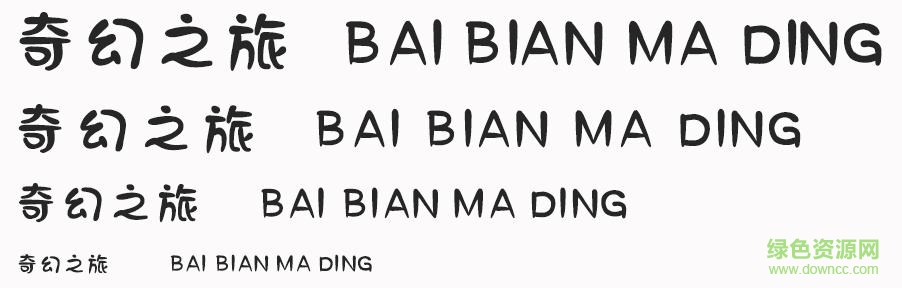
印品百變馬丁字體
印品百變馬丁字體是一款有印品字庫開發(fā)的動畫字體,喜歡看百變馬丁的朋友們不要錯過了,字里行間都是馬丁的氣息。還等什么,快來綠色資源網(wǎng)踴躍下載使用!
印品字庫攜手今日動畫IP百變馬丁,共同打造的首款同名動畫字體上線啦!充滿童趣的字形設(shè)計,處處體現(xiàn)《百變馬丁》突出的人物形象,為的就是讓粉絲有種見字如面的既視感。快來和馬丁開啟一段不一樣的奇幻之旅吧~